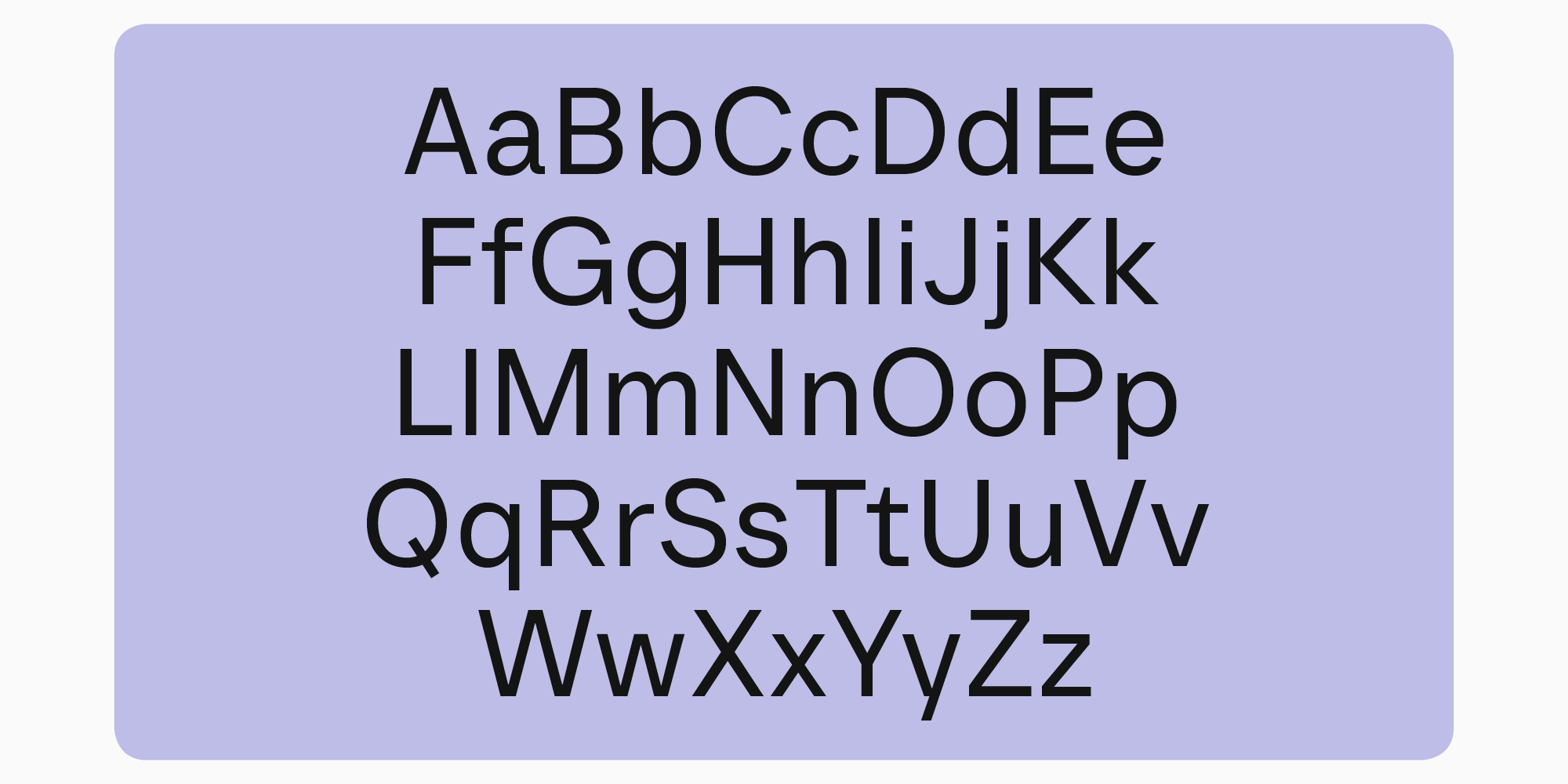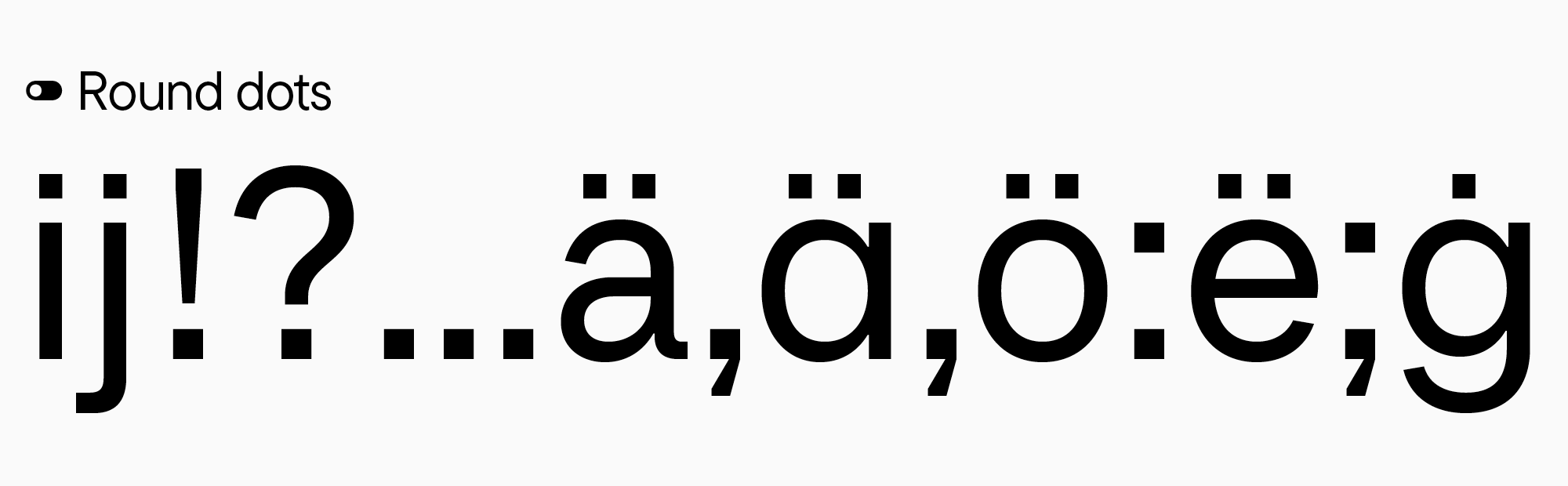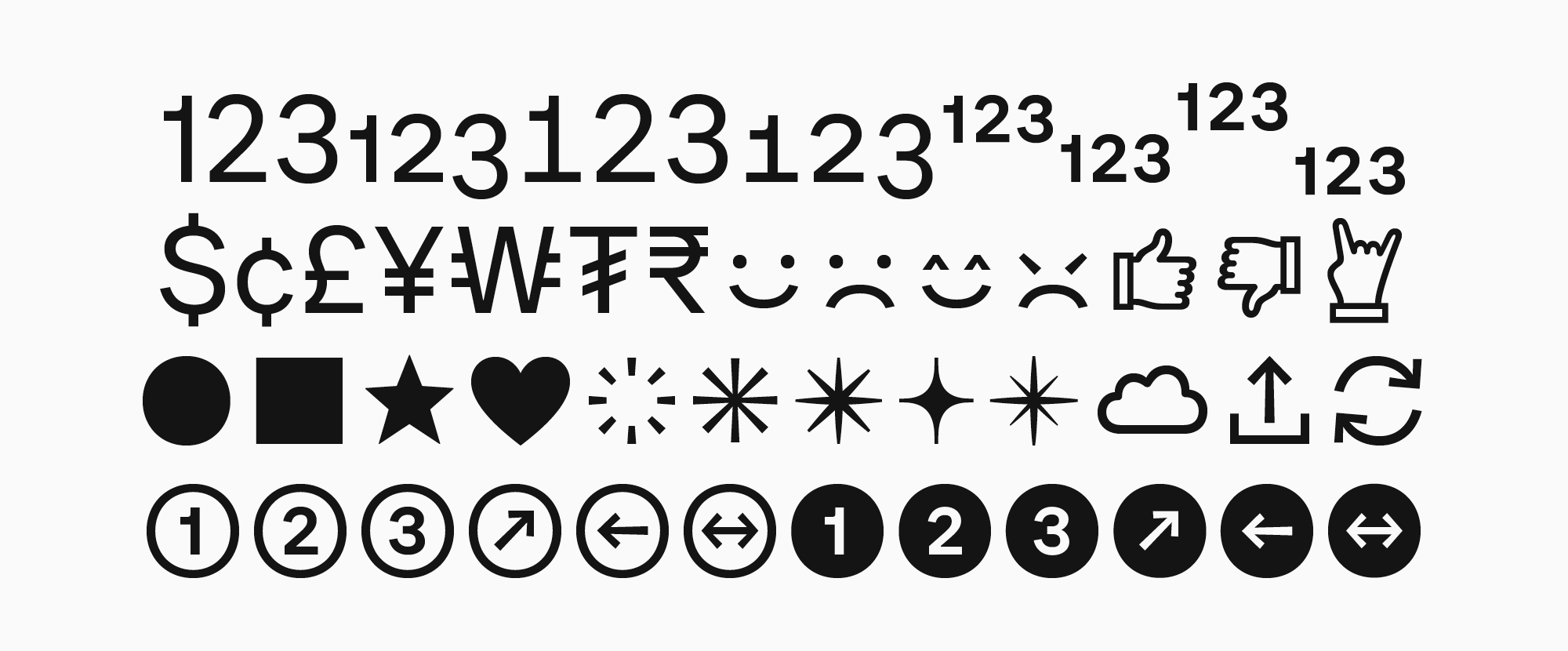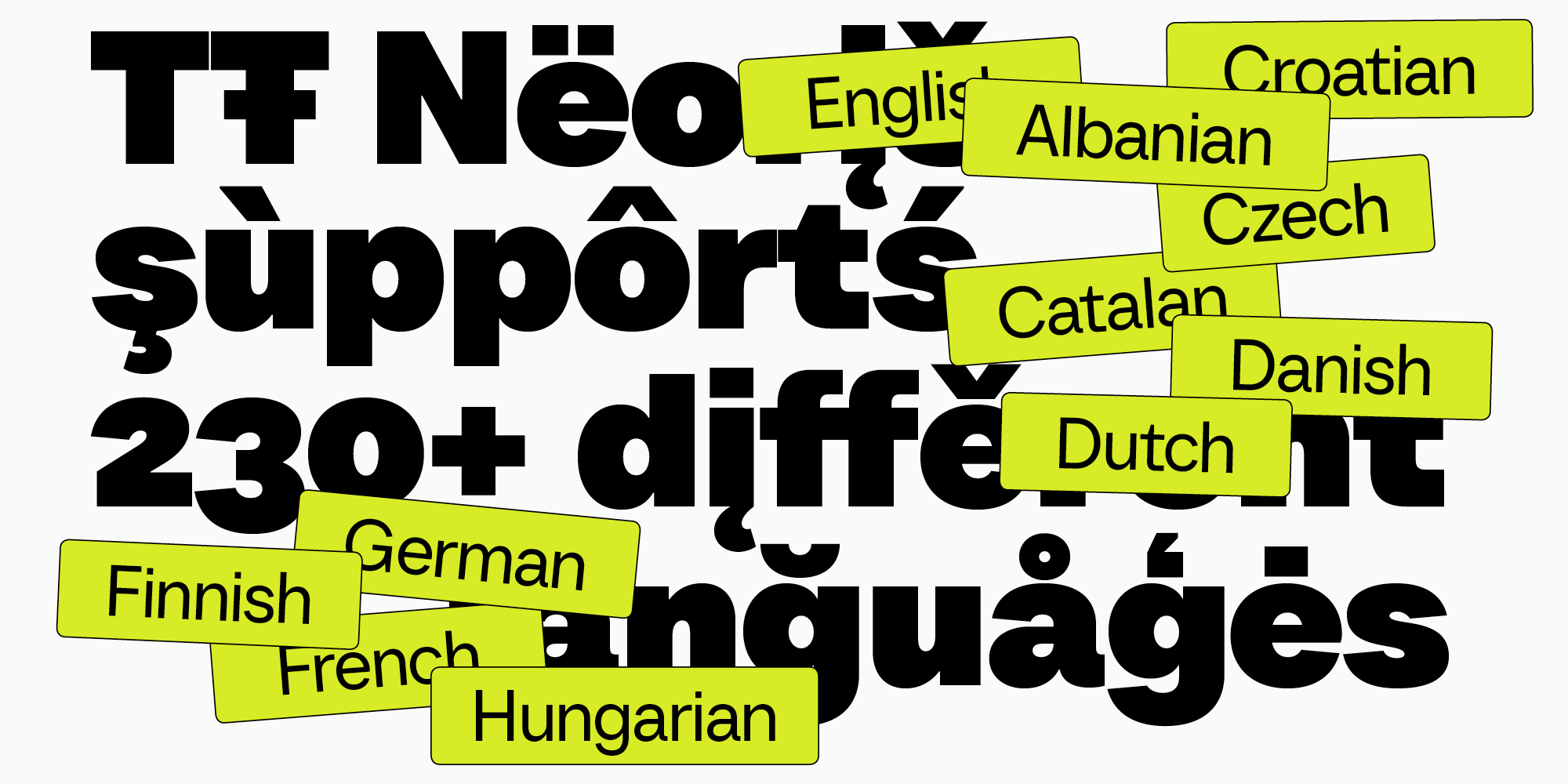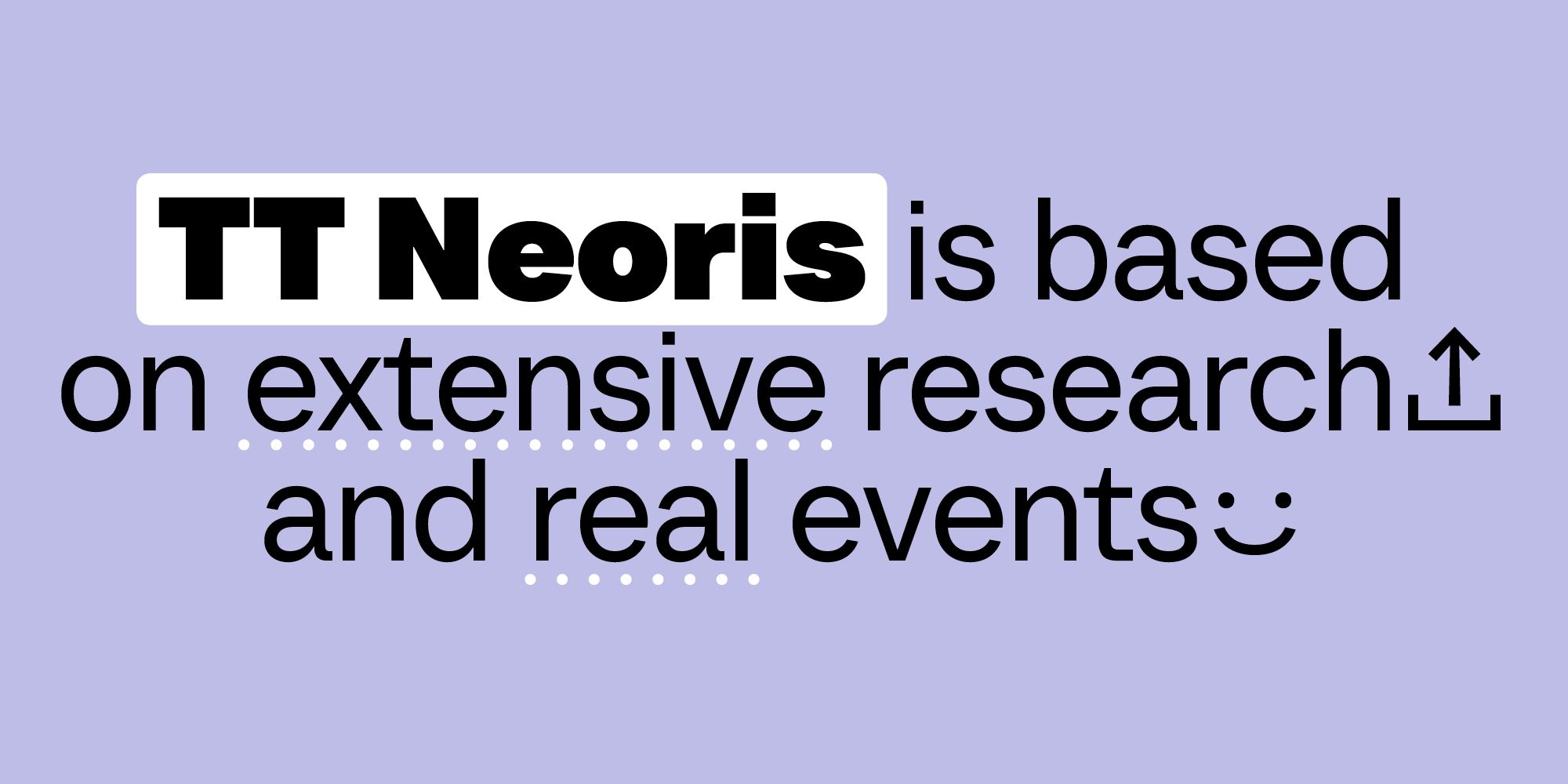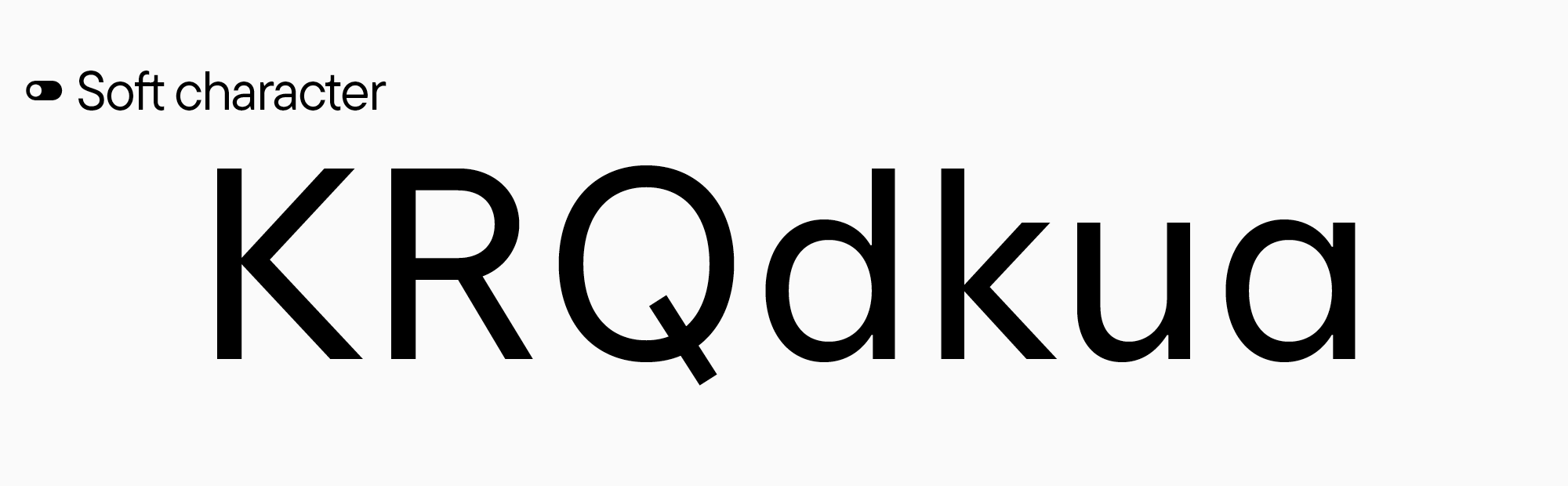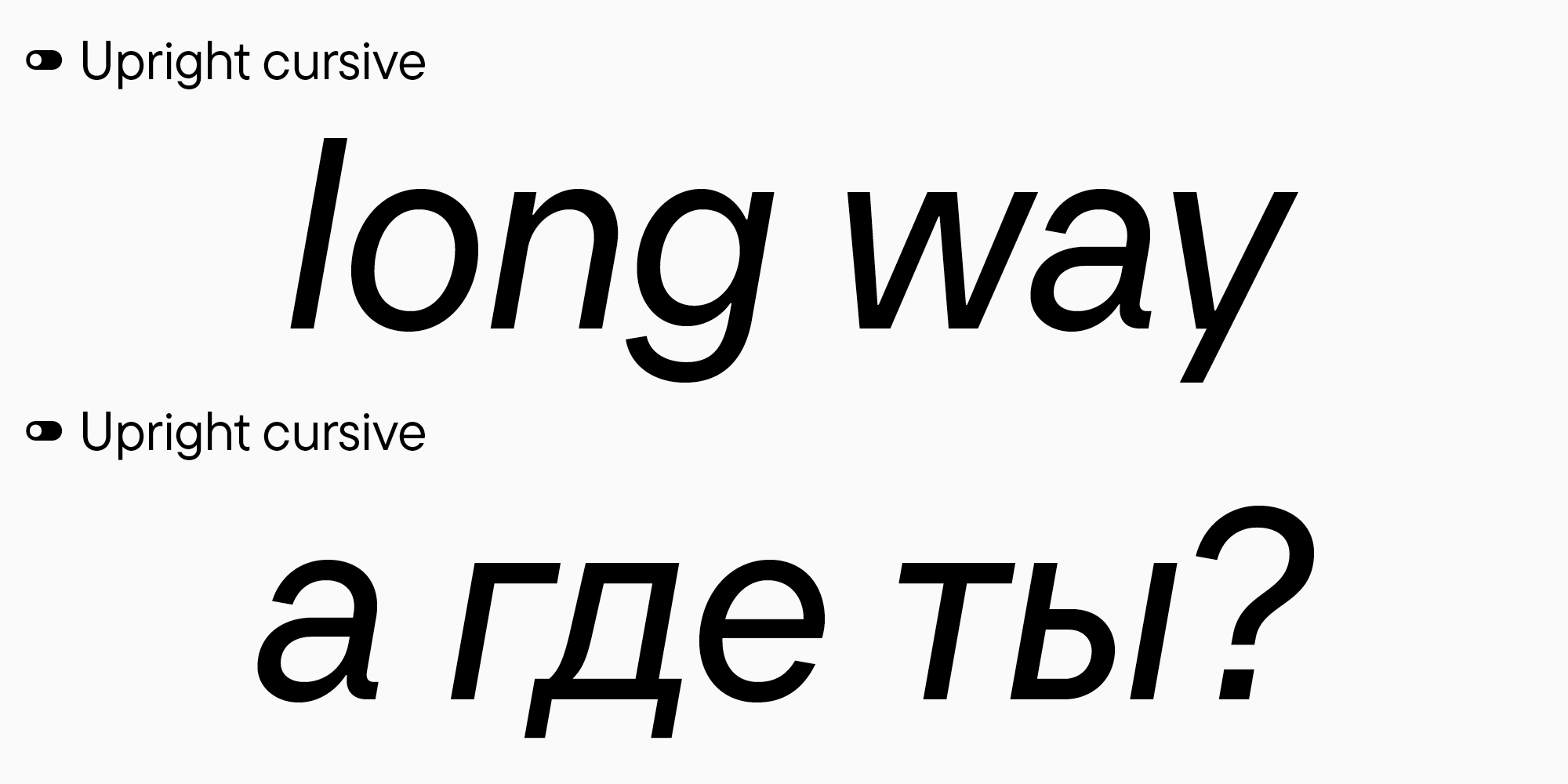
Шрифт маминой подруги: как создавался идеальный неогротеск TT Neoris
TT Neoris — шрифт от команды TypeType, вышедший в 2023 году. Название образовано из двух частей: neo, то есть «‎новый», и ‎rise — «‎восход». Его разработка длилась два с половиной года. На данный момент это самый амбициозный проект студии: мы поставили перед собой задачу создать идеальный неогротеск, который перевернет страницу в истории типографики и станет бестселлером.
Называя наш шрифт «идеальным», мы понимаем, что пространство для роста есть всегда и нет предела совершенству. Тем не менее мы сделали все, чтобы TT Neoris был достоин такого громкого определения: тщательно проработали каждый знак, создали объемный кассовый состав, настроили поддержку огромного количества языков, уделив особое внимание кириллическим. И, конечно, добавили большой набор OpenType фич, благодаря которым характер шрифта можно радикально менять и использовать одну гарнитуру вместо нескольких.
Все, что есть в этом шрифте, появилось не просто так: мы провели масштабное исследование, чтобы понять, в каком направлении развивается типографика, какие тенденции будут наиболее востребованы в будущем и чего не хватает пользователям в уже существующих гарнитурах.
Итак, предлагаем отправиться в путешествие по истории создания TT Neoris — неогротеска будущего!
Шаг первый: исследование рынка
Для начала ответим на логичный вопрос: а зачем вообще нужно было проводить исследование? Какие у него были цели и задачи?
Дело в том, что команда авантюристов TypeType решила создать «формулу любви» в мире шрифтов и проверить, можно ли спроектировать бестселлер, опираясь на точные расчеты. Мы решили попробовать повторить успех самых популярных шрифтов студии — TT Norms Pro и TT Commons Pro. И для этого нам нужно было понять, почему они так востребованы.
Стоит отметить, что мы делали исследования и раньше. Однако такое полное, осмысленное и глубокое — впервые.
«Любая популярность шрифта достаточно случайна, мы это уже видели на собственном опыте. Когда выходили TT Norms Pro и TT Commons Pro, мы не были готовы к тому, что эти гарнитуры станут мировыми бестселлерами. Но сейчас мы подошли к идее создания „идеального шрифта“ более осознанно. То есть четко поставили перед собой такую задачу и пошли с козырей — начали делать исследование».
«Нам было интересно проверить, работают ли наши исследования: мы захотели создать бестселлер и сделали все для того, чтобы это случилось. Но сработает ли это? Можно ли просчитать и предугадать популярность шрифта? Этого мы не знали».
Как мы уже сказали, наше исследование было масштабным. Оно включало анализ разных шрифтов-бестселлеров — от именитых с историческим прошлым до свежих хитов. В список «подопытных» вошли как, например, гарнитуры из коллекции Monotype, так и популярные шрифты независимых словолитен.
Шаг первый: исследование рынка
Мы замеряли все возможные параметры шрифтов, разбирали на составные части все знаки, конструкции, анализировали тип шрифта и его состав. Кроме того, спрашивали пользователей, какие шрифты им нужны и чего не хватает в существующих.
Опрос пользователей проводился с помощью вопросов открытого и закрытого типа. В частности, мы дали опрашиваемым возможность выразить дополнительные пожелания и попросили их указать свои любимые шрифты с пояснением о том, что именно им нравится.
В рамках исследования мы решили следующие задачи:
• Определили, шрифты какой группы наиболее востребованы и популярны: геометрические, гуманистические или механистические (под последними подразумеваются неогротески и максимально близкие к ним);
• Узнали, к какому историческому прототипу отсылает большинство бестселлеров;
• Выявили, какие шрифты наиболее привлекательны:
— равноширинные или разноширинные;
— узкие, средние или широкие;
— с закрытой, открытой или средней апертурой;
— с выраженным, малозаметным или отсутствующим контрастом;
— с вертикальными, горизонтальными или средними срезами;
— с квадратными, средними или круглыми овалами;
— с простым наклоном или аутентичными италиками;
— с брутальным, мягким или нейтральным характером;
— с двухчастной или одночастной конструкцией букв «а» и «g»;
— «I» должна быть прямой или с крючком;
— с отличительной графикой или без неё.
• Спросили у пользователей, какие характеристики влияют на их решение приобрести шрифт, должен ли шрифт иметь схожие параметры с другими шрифтами, какие языки и дополнительные знаки им необходимы, важен ли для них вариативный шрифт и какие проблемы они видят в существующих шрифтах;
• Изучили количество начертаний и подробно разобрали знаковый состав бестселлеров.